8 tipografías para logos que te inspirarán
¿Buscas la tipografía perfecta para tu logo? Descubre 8 fuentes inspiradoras que llevarán el diseño de tu logotipo al siguiente nivel.
A la hora de hacer un nuevo logo para nuestra marca, hay varios factores que es importantísimo tener en cuenta. Algunos de ellos son más llamativos, como el color y la forma, y otros pueden pasar más desapercibidos.
Una de las características más relevantes de un logo es la tipografía. Existen infinidad de tipos de letras y, si no tenemos mucha idea de diseño gráfico, podemos pensar que elegir la correcta es tan fácil como escoger la que más te guste. Pero la letra dice mucho de tu marca, tiene que estar en sintonía con lo que estás vendiendo y con el público al que te estás dirigiendo, por eso es muy importante no tomar esta decisión a la ligera.
En este artículo, te vamos a contar algunos de los mejores tipos de letras para logos. Descúbrelos y elige el que más se adapte a tu marca.
Raleway
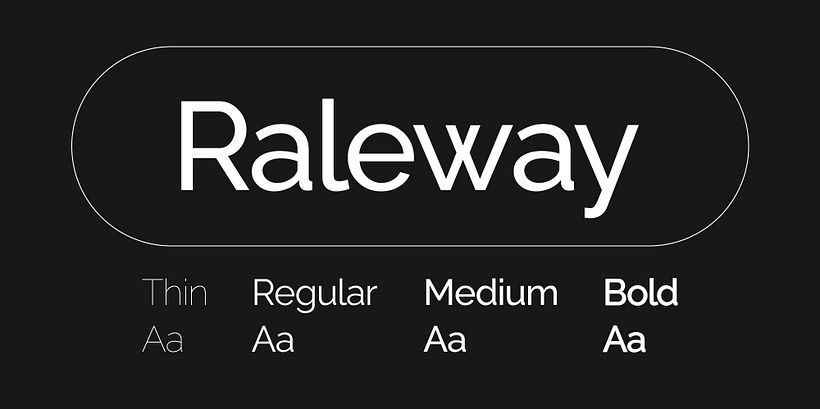
La tipografía Raleway es como la artista versátil del mundo de las letras. Con una elegancia moderna, sus formas geométricas ofrecen un equilibrio perfecto entre lo contemporáneo y lo clásico. Cada trazo cuenta con una línea cuidadosamente diseñada para transmitir simplicidad y estilo, haciendo que las palabras cobren vida con gracia y claridad. Es la elección ideal para proyectos que buscan una estética pulida y legible, sin sacrificar el toque vanguardista.
Futura
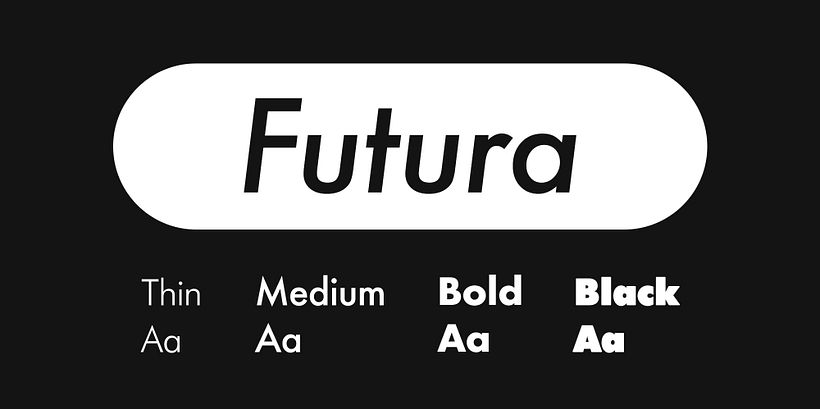
Futura es un equilibrio magistral entre lo clásico y lo vanguardista. Con líneas geométricas y proporciones perfectas, cuenta con un diseño elegante que le confiere una apariencia moderna sin perder la gracia de la tradición. La simplicidad de Futura es su mayor virtud, ya que proporciona legibilidad y claridad excepcionales en cada palabra. En definitiva, es la elección ideal para quienes buscan una estética sofisticada y contemporánea con un toque de atemporalidad.
Poppins
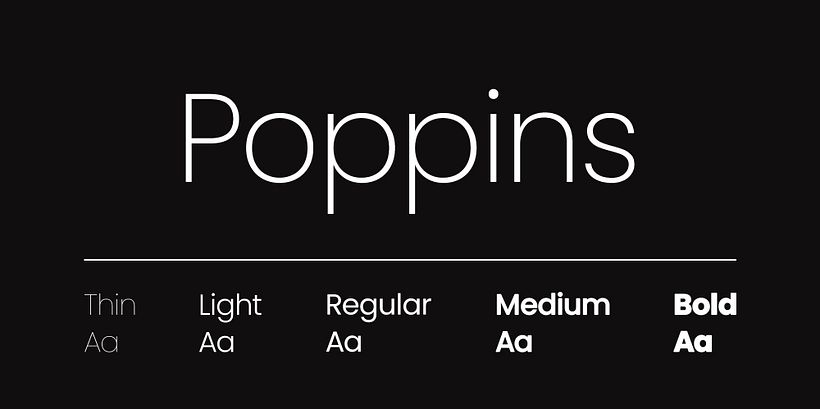
Poppins es un tipo de letra para logos que emana vitalidad y modernidad. Con su diseño geométrico y líneas pulcras, cada característica se presenta como un lienzo en blanco para expresar tu identidad con una estética contemporánea. Su estilo es un soplo de aire fresco, adaptable y versátil, capaz de integrarse en diversos diseños sin perder su distintivo carácter. Poppins se convierte en la aliada que aporta elegancia y simplicidad, transformando tu logo en una declaración visual duradera. La elección ideal para transmitir una imagen contemporánea y dinámica con un toque de sofisticación intemporal.
Helvetica
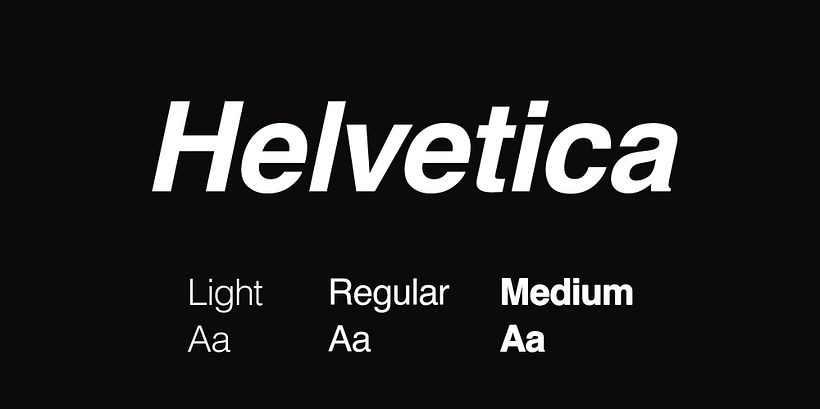
Helvetica es la esencia misma de la elegancia tipográfica en un logo. Sus líneas limpias y su equilibrio perfecto ofrecen una simplicidad que trasciende el tiempo. Cada letra, con su forma geométrica, es como un pilar de claridad y legibilidad. Es la elección atemporal para un logo y confiere una estética moderna y versátil. Helvetica se presenta como la confidente de diseño, aportando una presencia fuerte y sin pretensiones. Cada trazo es una afirmación de la simplicidad sofisticada y asegura que tu logo destaque con una elegancia discreta pero poderosa en cualquier contexto.
Garamond
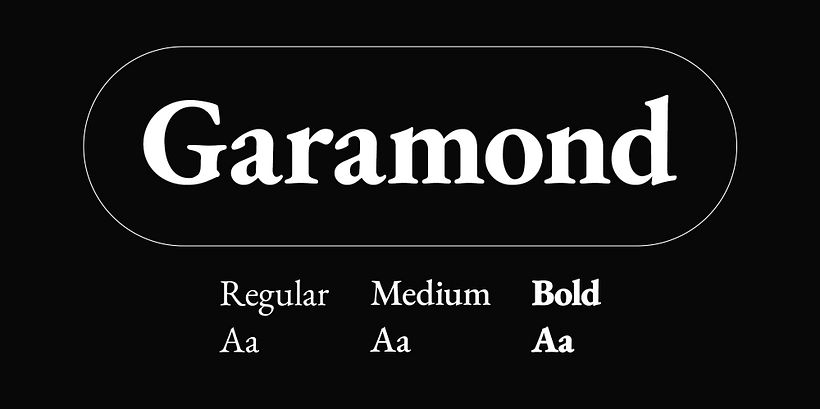
Garamond para un logo es un equilibrio perfecto entre la elegancia clásica y la legibilidad moderna. Sus trazos finos y proporciones equilibradas dan a cada letra una estética refinada y atemporal. La tipografía Garamond aporta una sensación de autoridad sutil, perfecta para logos que buscan transmitir un toque de tradición y seriedad. Cada característica, desde las curvas delicadas hasta los detalles precisos, se combina para crear una identidad visual distintiva que destaca por su elegancia duradera. Garamond es la elección ideal para logos que buscan una estética sofisticada con un toque de historia.
Univers
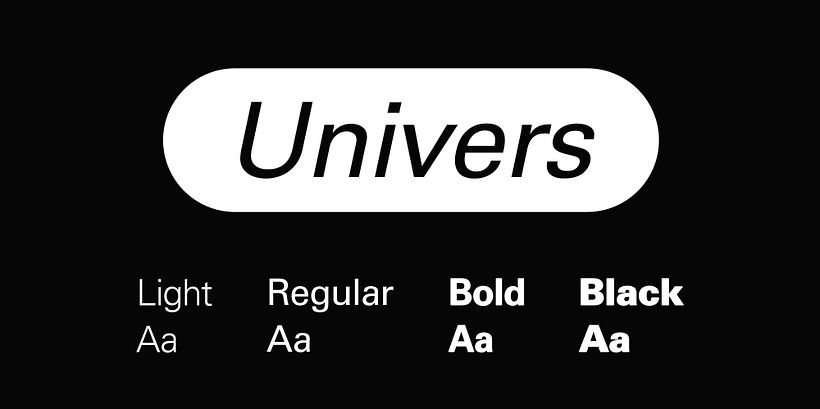
Univers se caracteriza por líneas limpias y proporciones equilibradas, que aportan una estética moderna y pulcra. Cada letra es una representación de simplicidad y claridad, con una versatilidad que se adapta a diversos estilos sin perder su elegancia distintiva. Esta tipografía ofrece una presencia fuerte y confiable, siendo una elección segura para aquellos que buscan una estética contemporánea y atemporal en su logo.
Proxima Nova
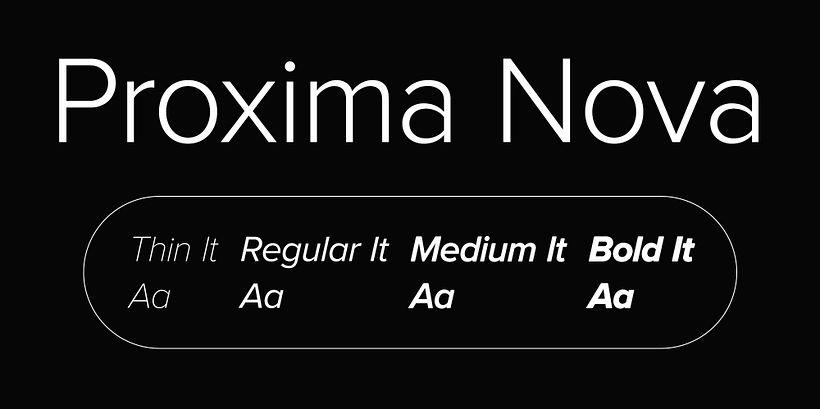
Proxima Nova en un logo es la elegancia contemporánea en su máxima expresión. Con líneas limpias y una estética moderna y geométrica, cada letra es una fusión perfecta de simplicidad y estilo. Es la aliada ideal para marcar una presencia fuerte y moderna en el diseño del logo. Proxima Nova ofrece una legibilidad excepcional y una versatilidad que se adapta a diversos contextos visuales. Es la elección perfecta para quienes buscan transmitir una imagen fresca y actual, donde cada trazo contribuye a crear una identidad visual única y memorable.
Roboto Slab
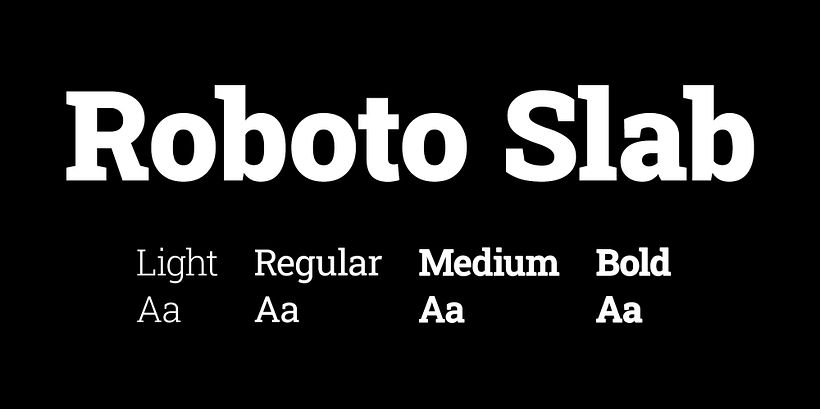
Roboto Slab es la fusión perfecta de robustez y modernidad. Cada letra presenta líneas sólidas y contornos definidos, creando una estética contemporánea con un toque de fortaleza clásica. Es la elección audaz para un logo que busca destacar con confianza. Roboto Slab aporta una legibilidad excepcional, combinada con una presencia fuerte que resiste el paso del tiempo. Cada trazo es una declaración visual que transmite una mezcla entre solidez, modernidad y elegancia.